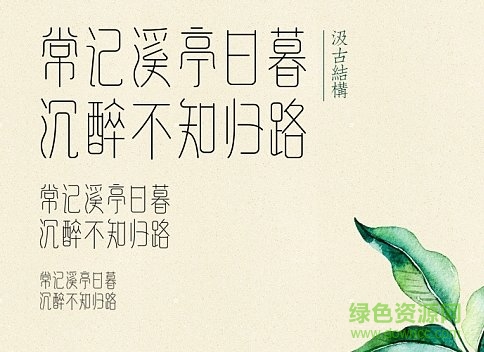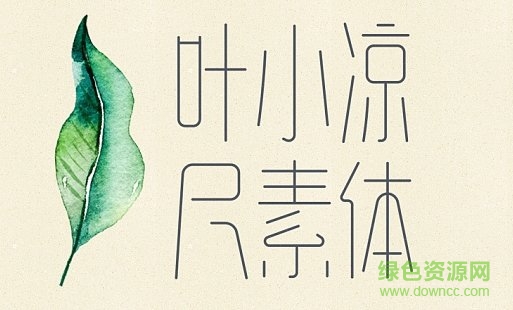
葉小涼尺素體是一款十分具有藝術(shù)美感的現(xiàn)代時(shí)尚字體,清雅的復(fù)古風(fēng),讓字跡充滿古風(fēng)恬淡優(yōu)雅的韻味,給人氣質(zhì)溫潤爾雅的視覺美感,喜歡的朋友就來綠色資源網(wǎng)試試吧!
一個(gè)等線體,取篆意,筆畫圓直。
字形均勻憑證,通適于標(biāo)題裝飾,機(jī)構(gòu)上微緊下略松,有挺立之姿。
古有詩云:猶冀蒼雁赬鯉,時(shí)傳尺素;清風(fēng)明月,俱寄相思。
故名“尺素”。